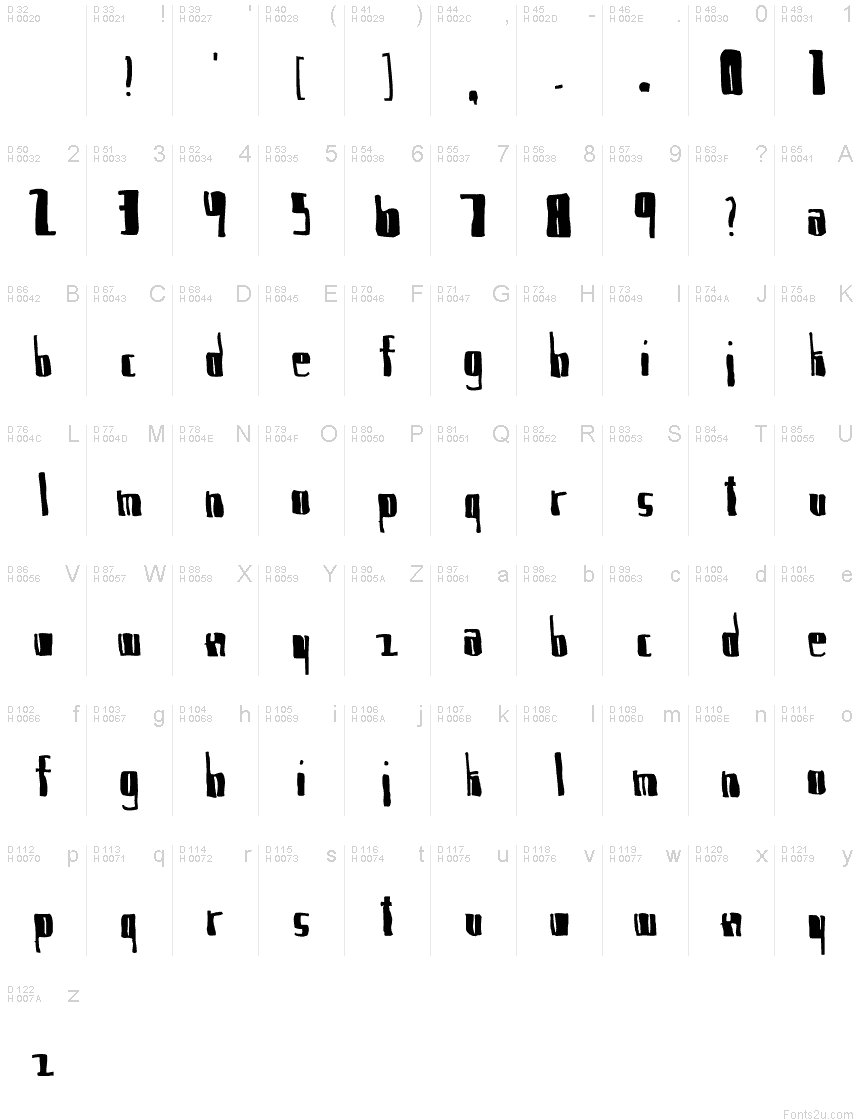
I am Nervous od Candyfingers to darmowy, zniekształcony krój displayowy o drżącej, surowej energii. Każda litera wygląda na lekko spuchniętą i rozmytą na krawędziach, jakby została odbita drżącą ręką, co nadaje słowom niepokojący, nerwowy puls. Odstępy między znakami są celowo ciasne i duszne, przez co litery niemal wibrują na stronie.
I am Nervous pozwala natychmiast nadać niepokojący klimat plakatom horrorów, zinom undergroundowym, okładkom płyt punkowych, glitchowym miniaturom na YouTube czy mrocznym tytułom gier. Ten darmowy font najlepiej sprawdza się w dużych rozmiarach, gdzie jego nierówne krawędzie i chaotyczny rytm naprawdę przykuwają uwagę. W tekście głównym połącz go z prostym, wąskim krojem bezszeryfowym, aby zachować wyrazisty, a jednocześnie czytelny charakter projektu.